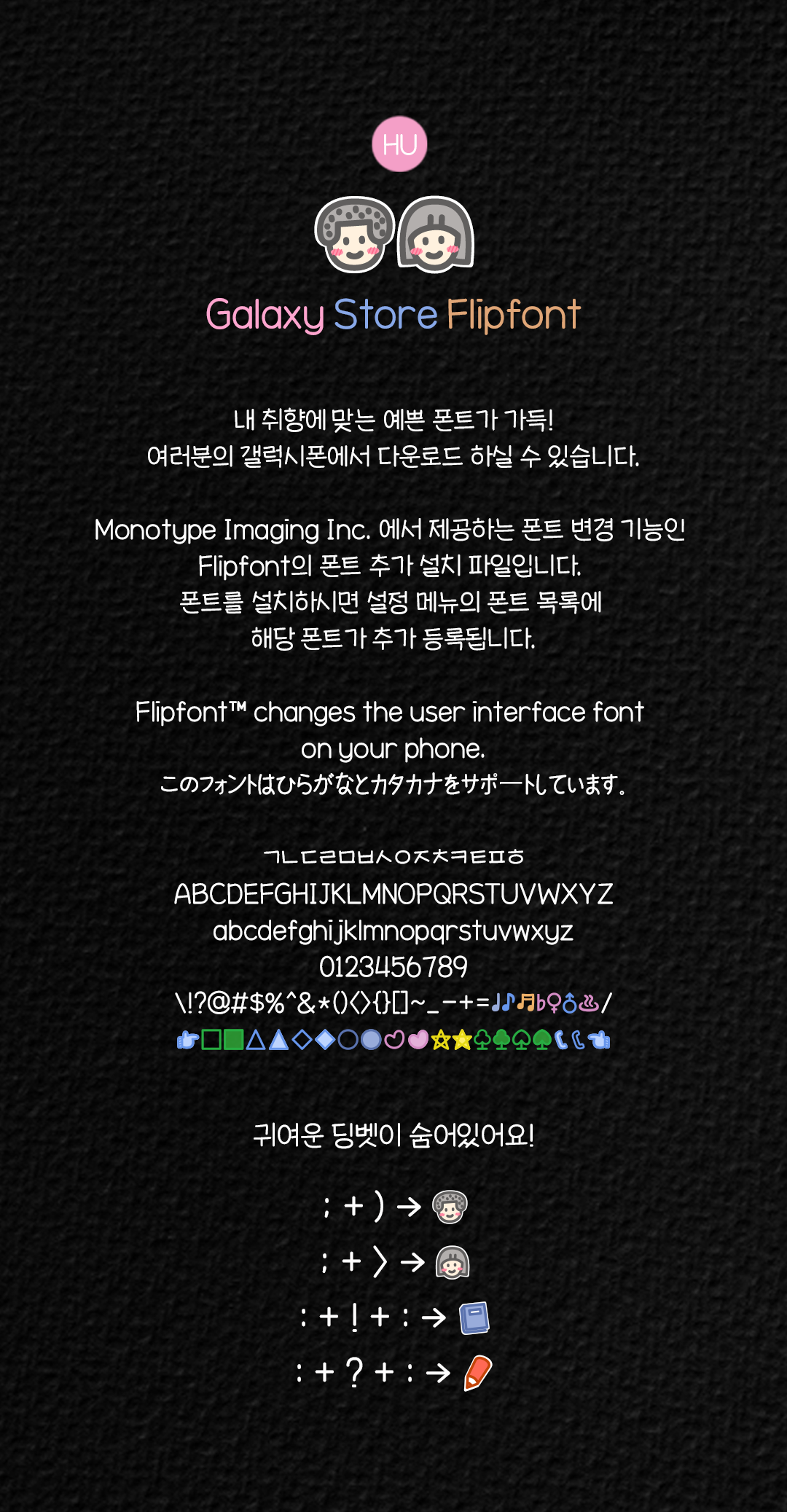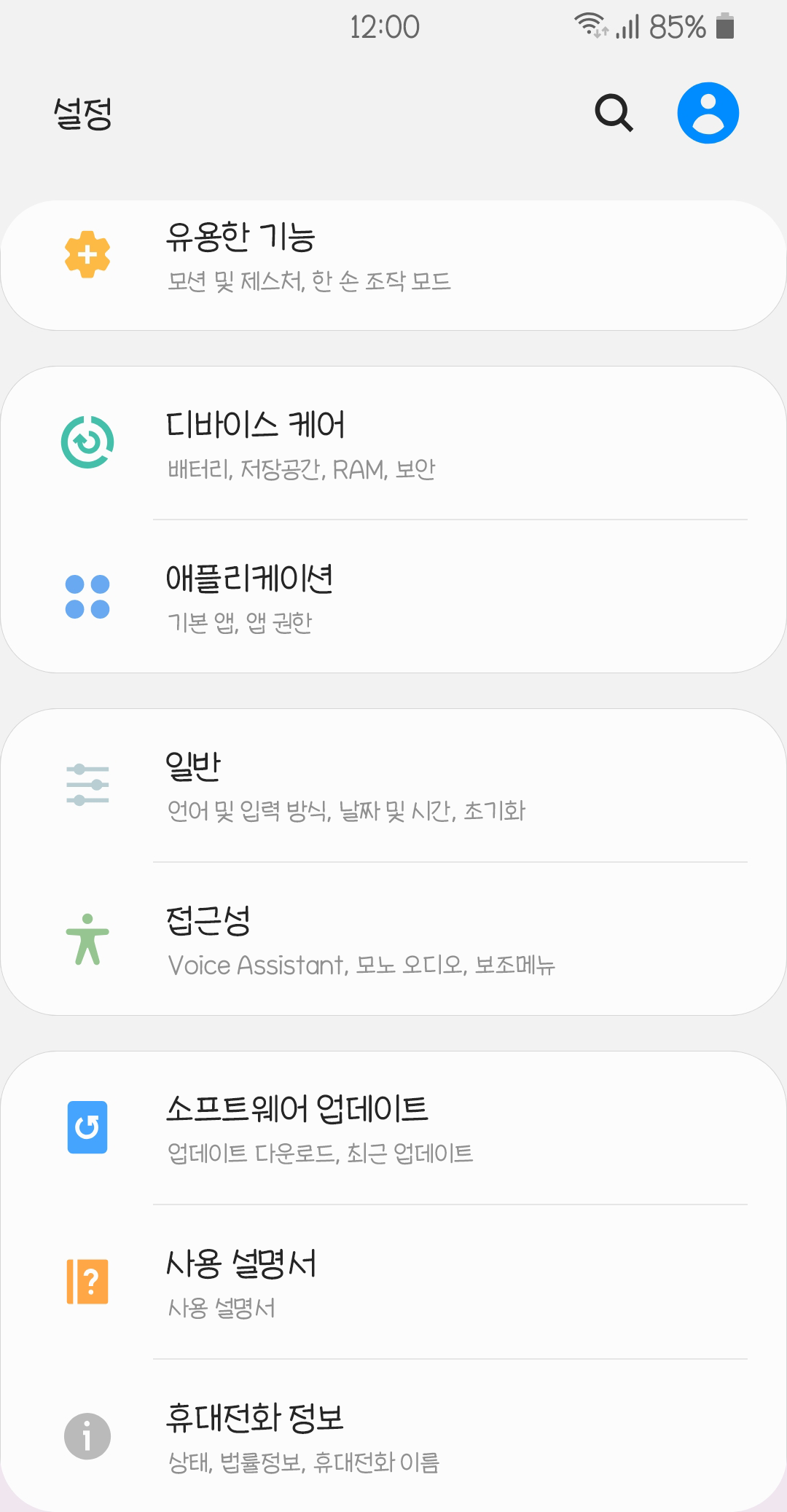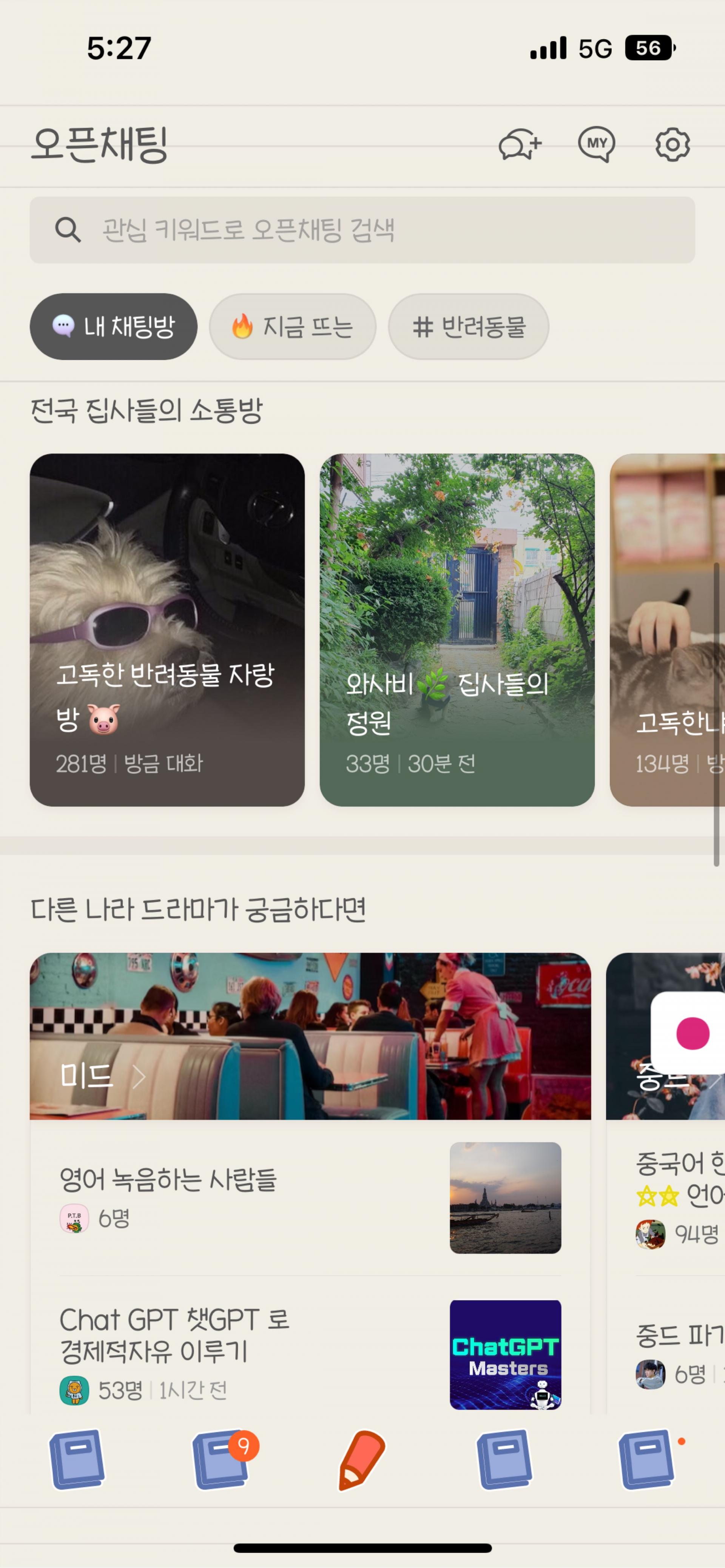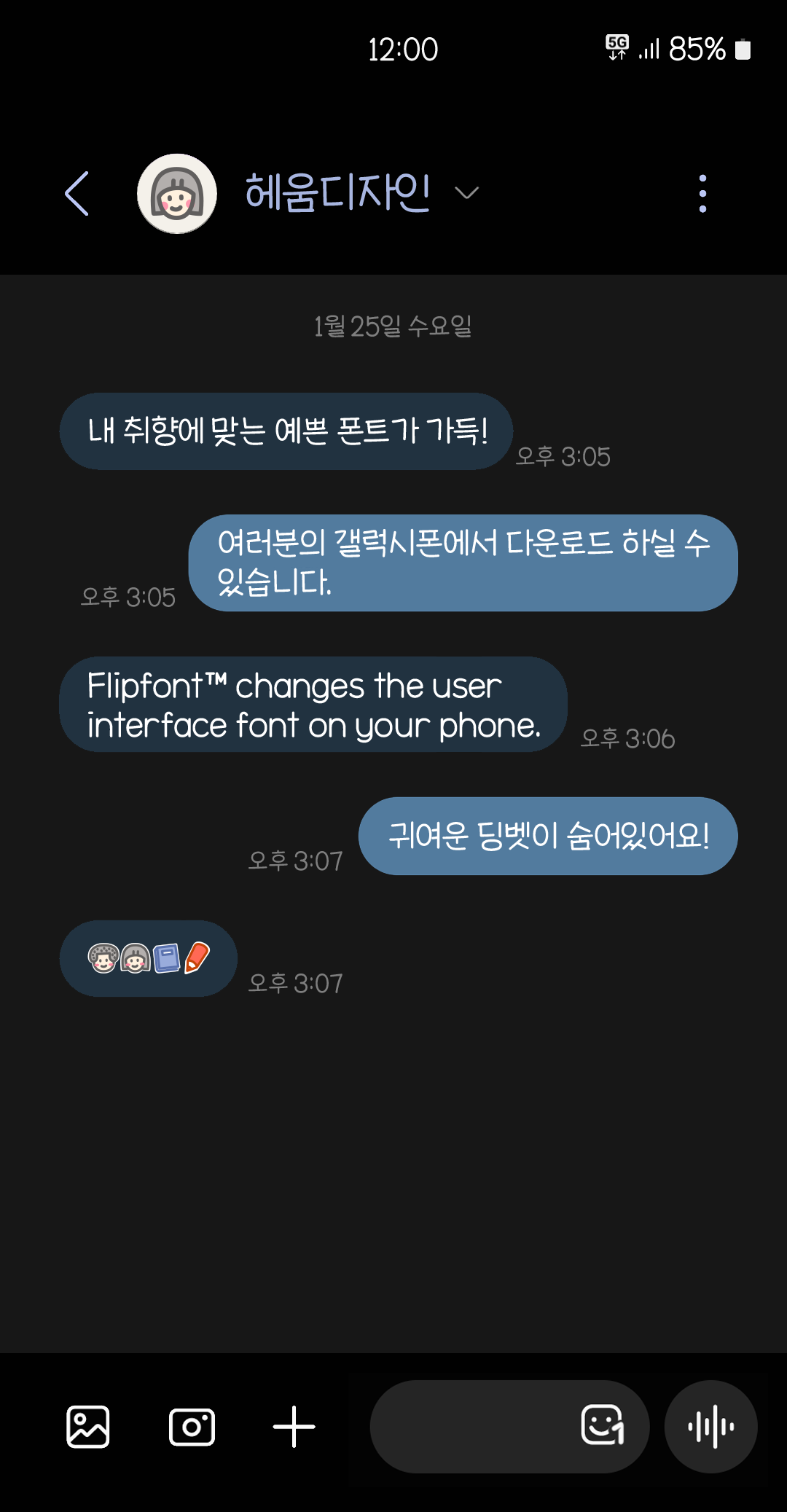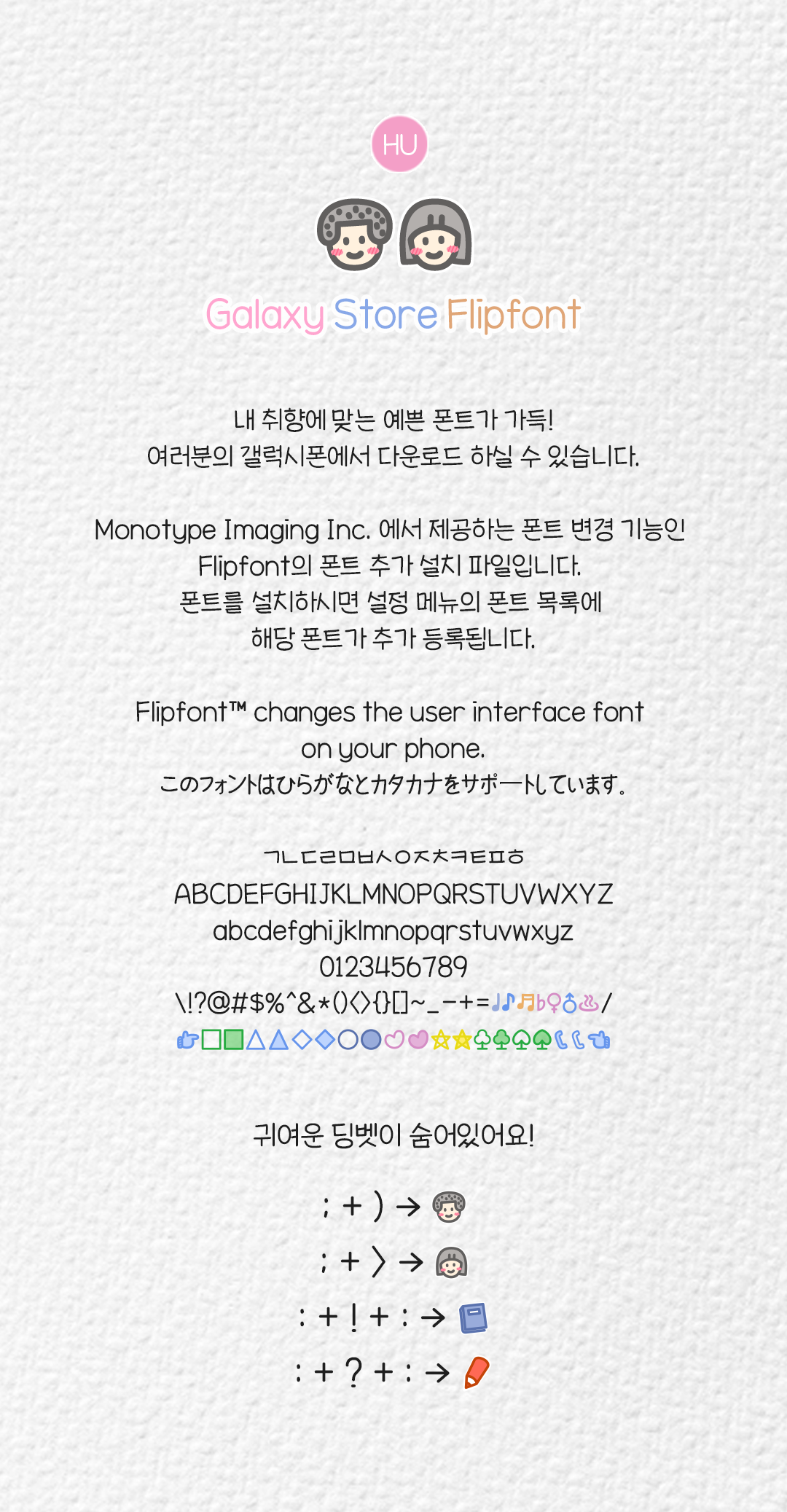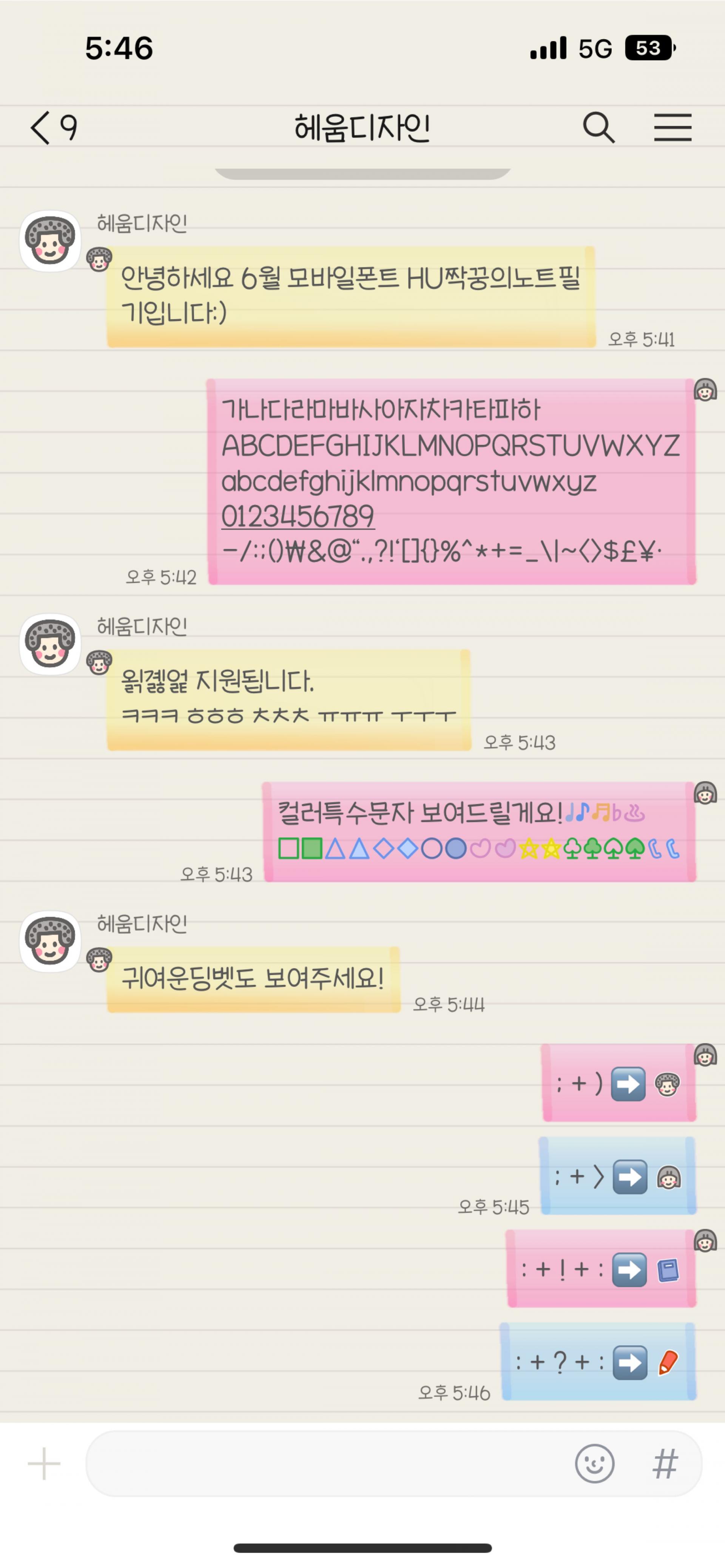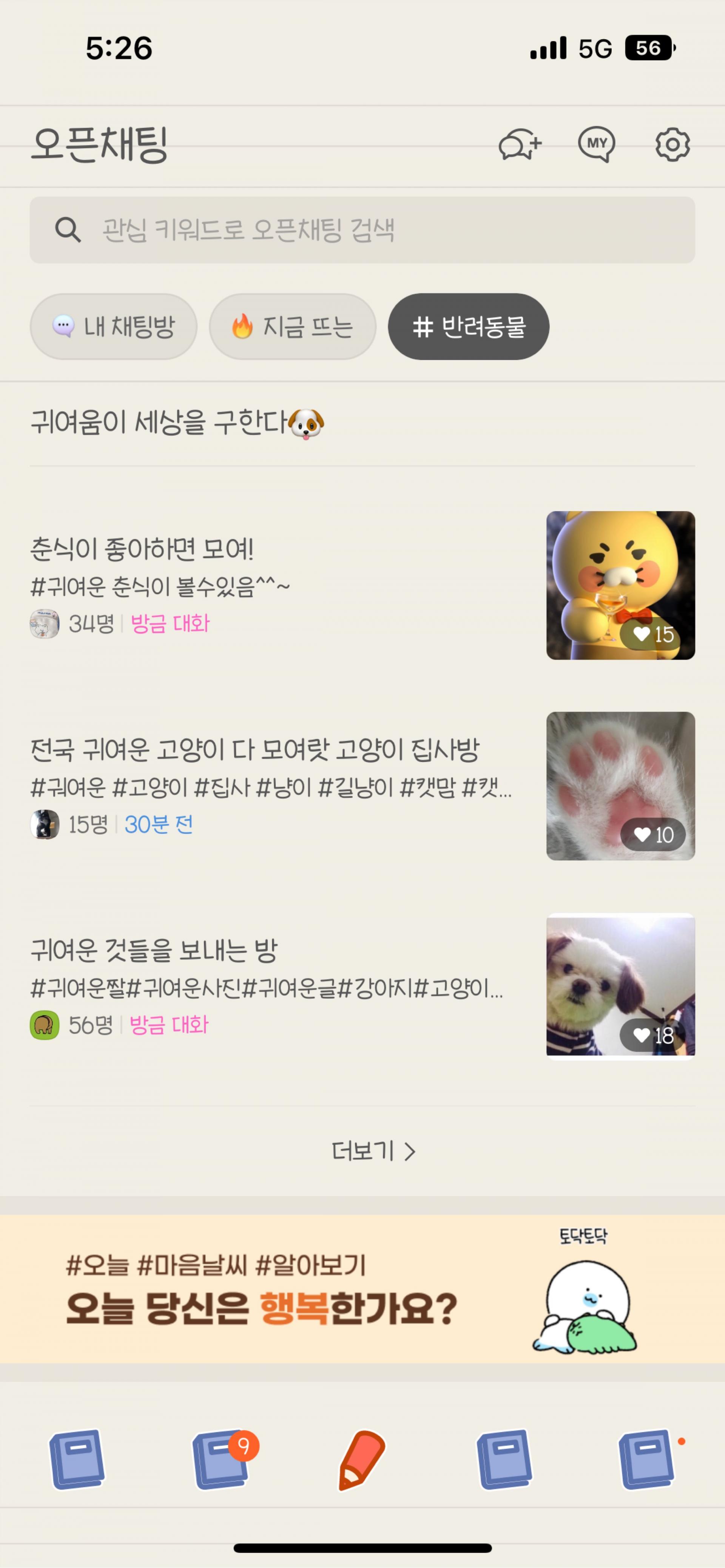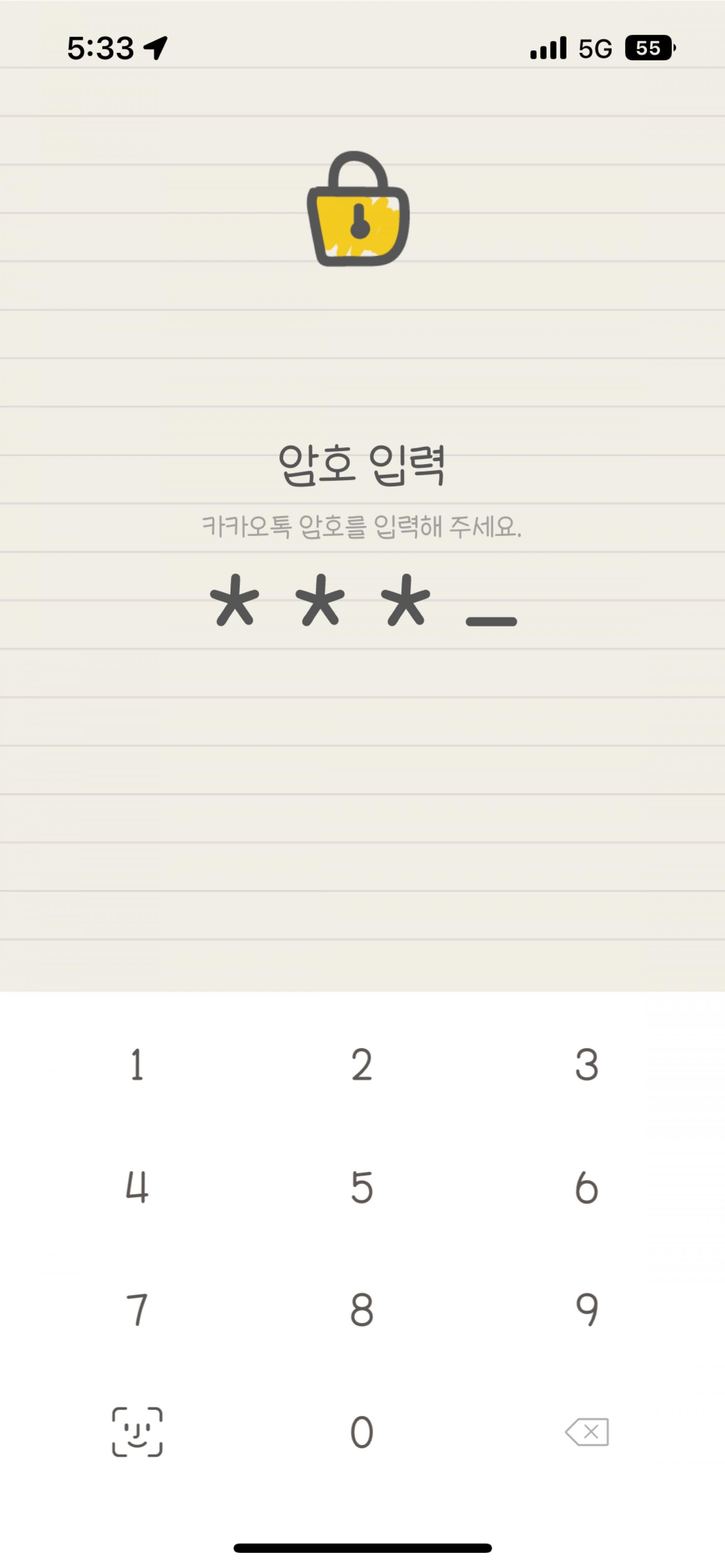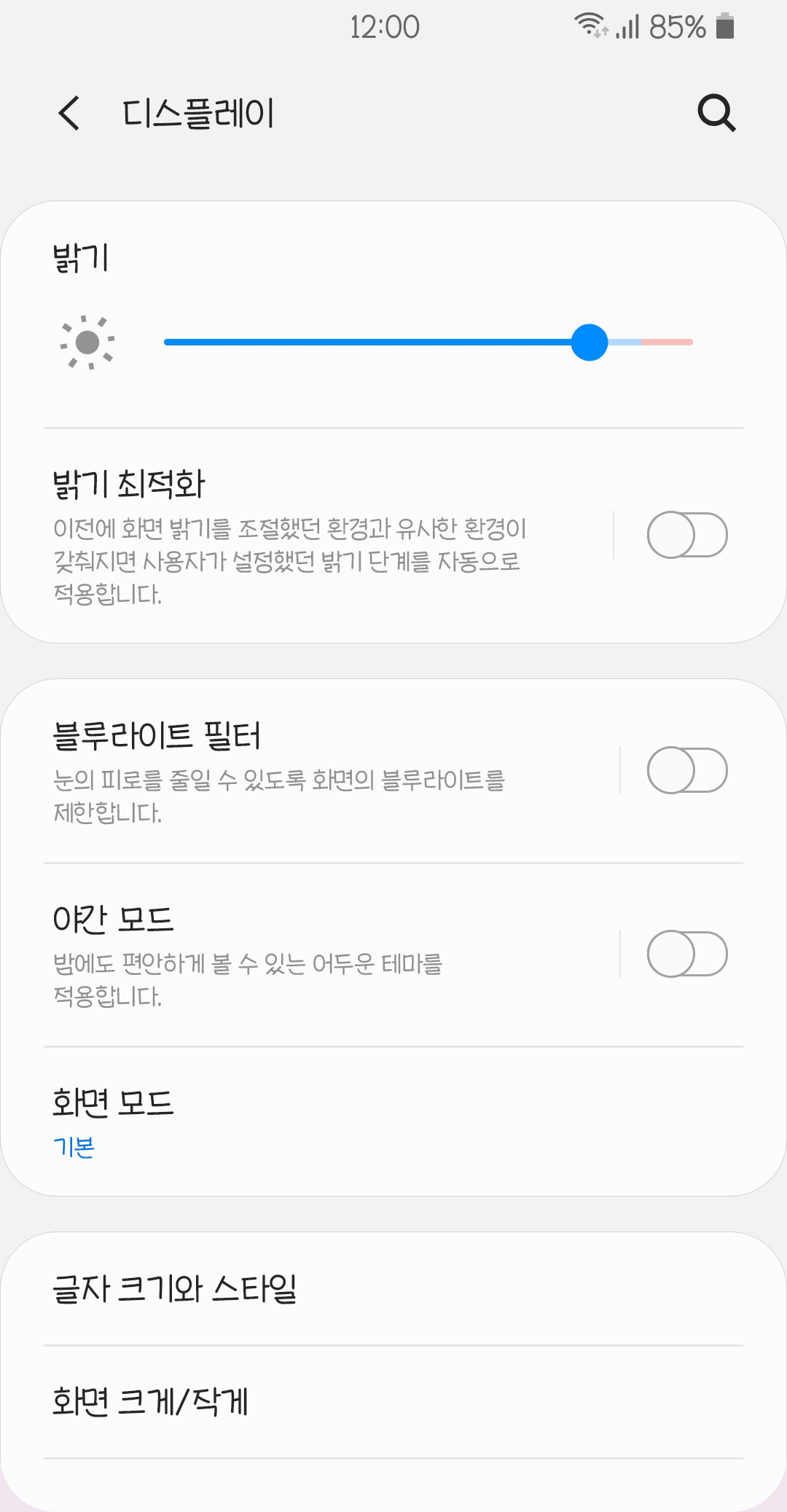
6월 모바일폰트 "짝꿍의노트필기"가 출시 되었습니다!
0.7mm 펜으로 쓴 듯한 노트필기에 어울리는 서체입니다.큰 자소와 손글씨 폰트를 선호하시는 분들께 추천드립니다.
6월 모바일폰트 "짝꿍의노트필기"가 출시 되었습니다!
0.7mm 펜으로 쓴 듯한 노트필기에 어울리는 서체입니다.
큰 자소와 손글씨 폰트를 선호하시는 분들께 추천드립니다.